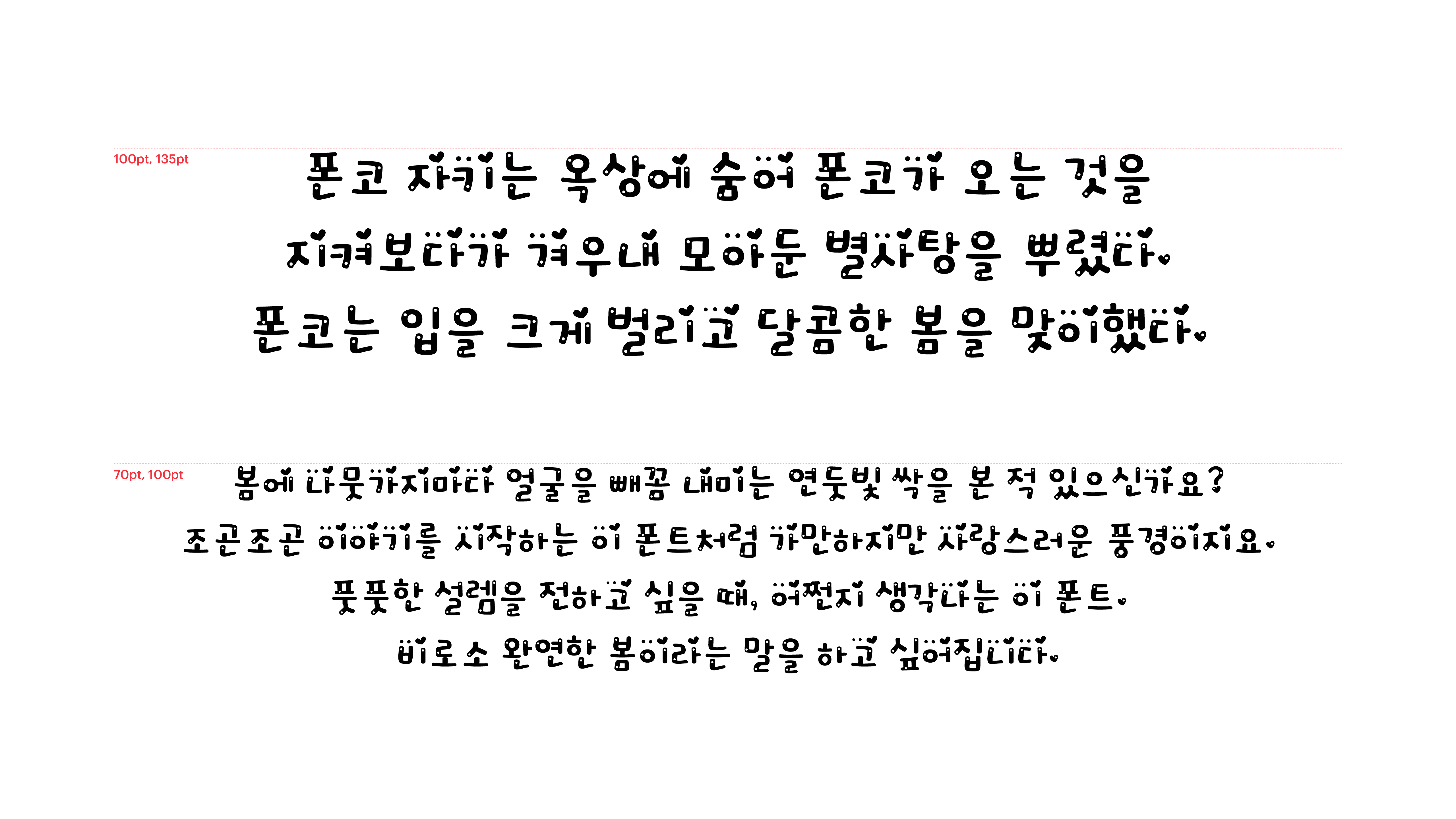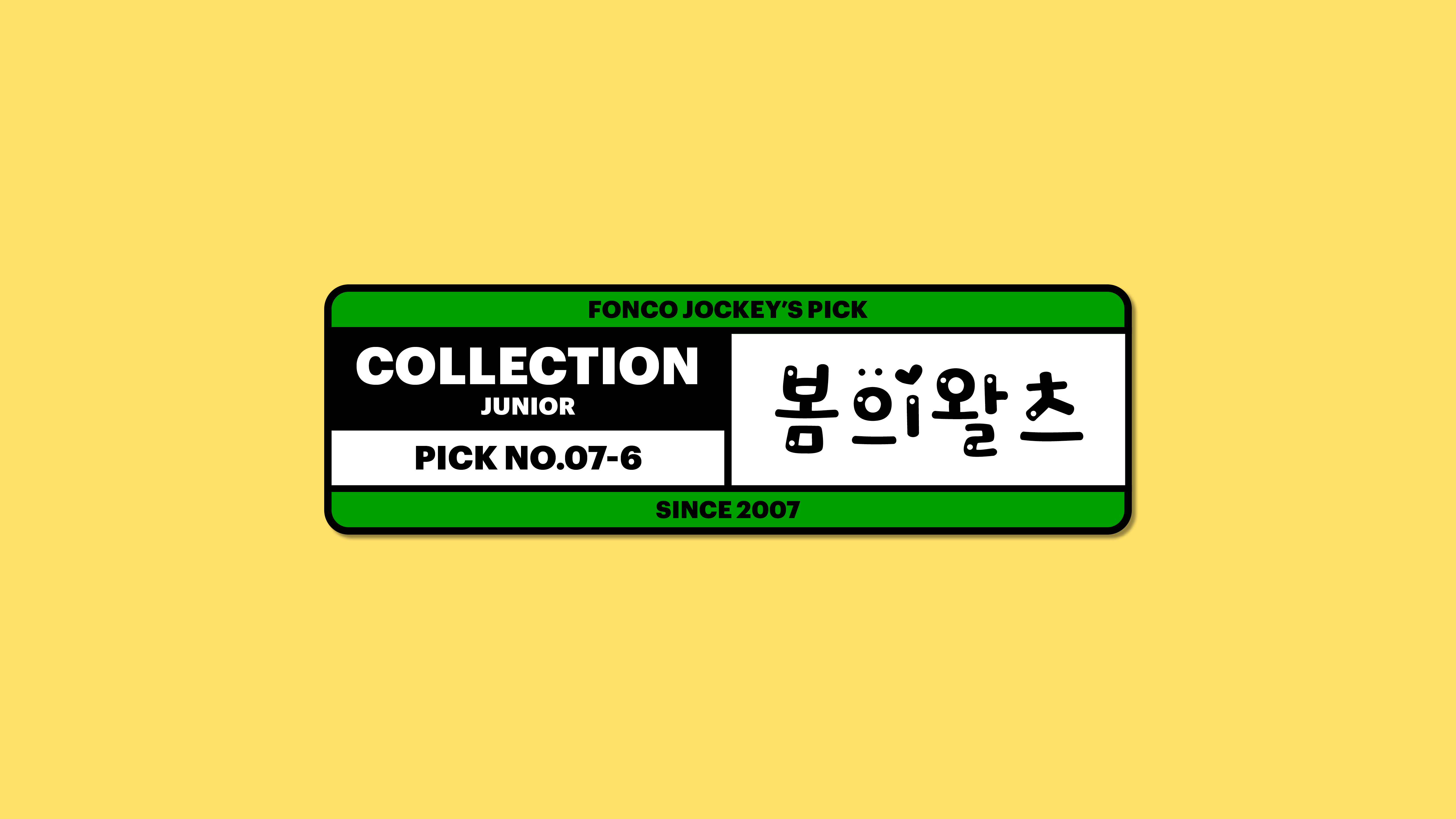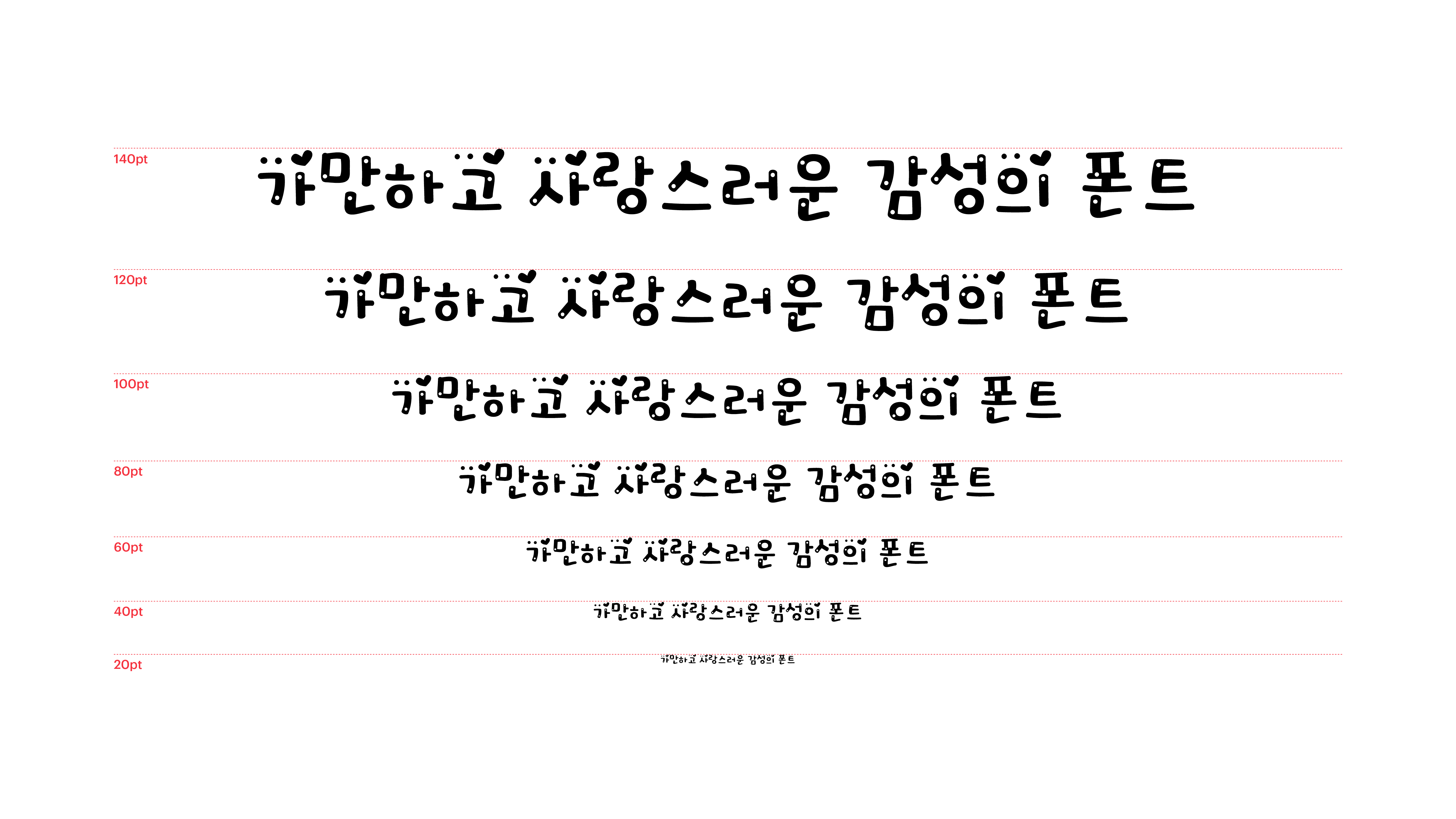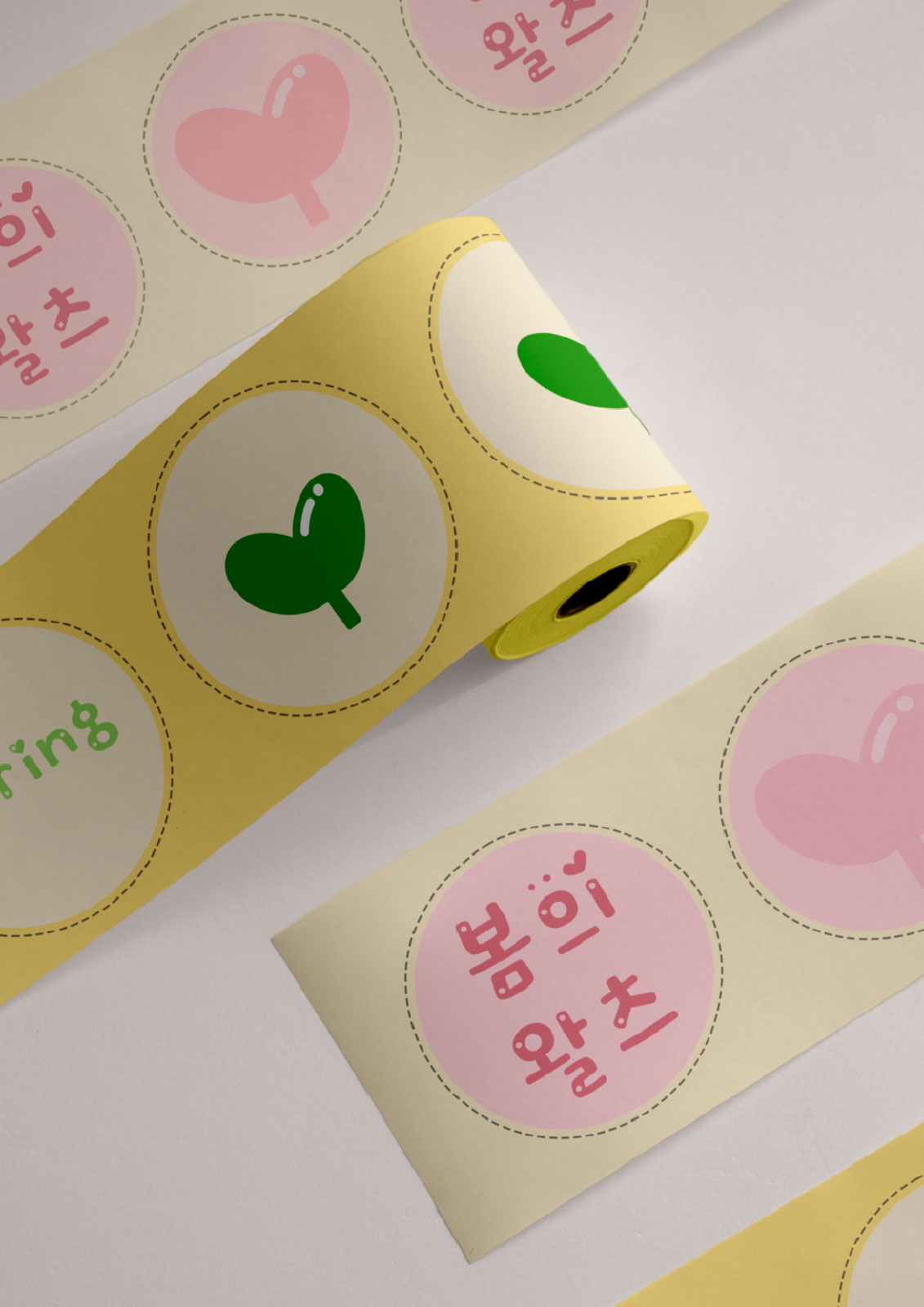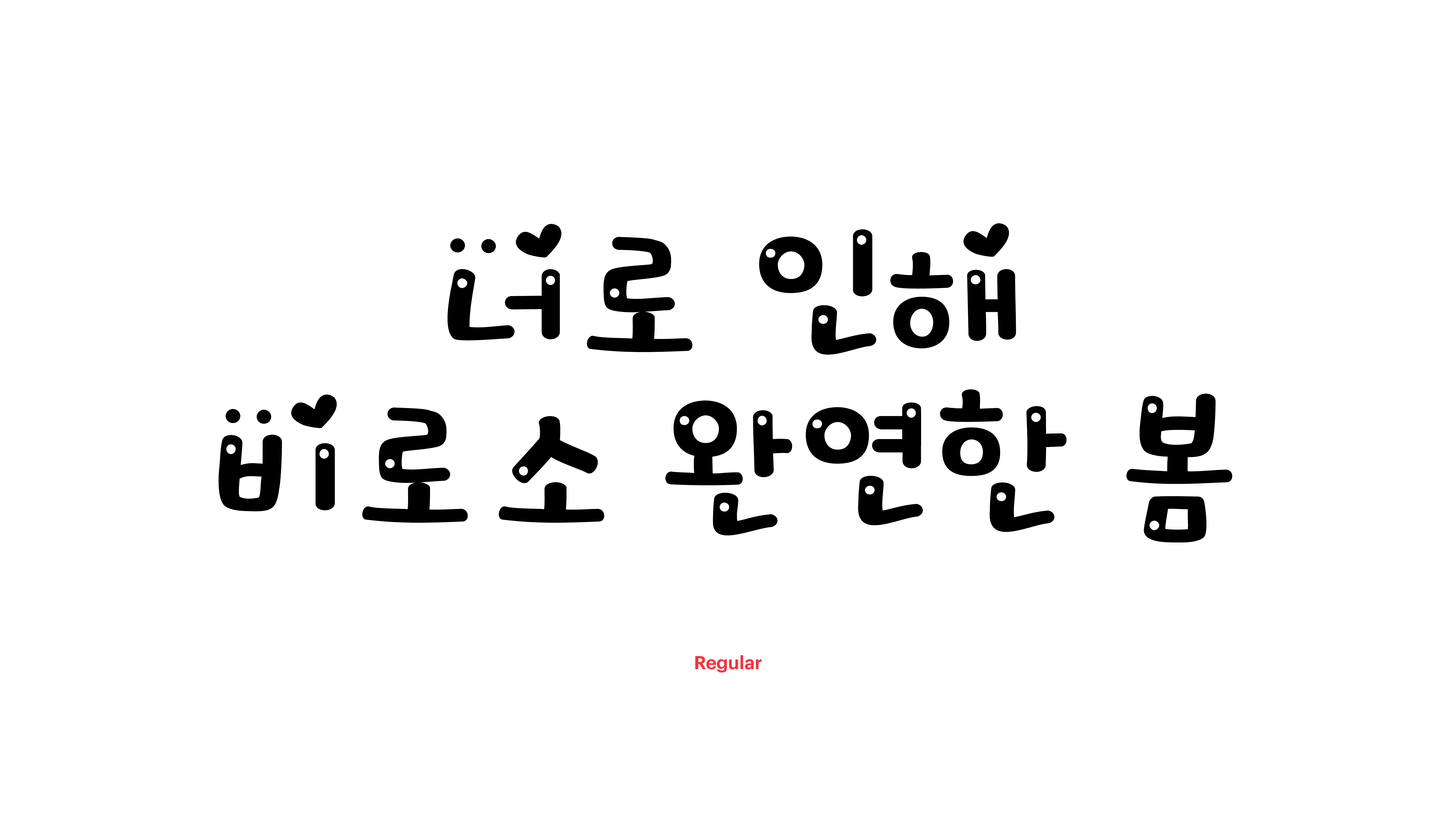
봄의왈츠
Yoon 봄의왈츠
봄에 나뭇가지마다 얼굴을 빼꼼 내미는 연둣빛 싹을 본 적 있으신가요? 조곤조곤 이야기를 시작하는 이 폰트처럼 가만하지만 사랑스러운 풍경이지요. 풋풋한 설렘을 전하고 싶을 때, 어쩐지 생각나는 이 폰트. 비로소 완연한 봄이라는 말을 하고 싶어집니다.